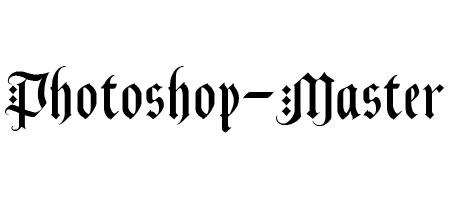
Дополнения Шрифты Татьяна Гапонова 25 июля 2009 Шрифт - BlackKnightFLF Красивый шрифт без поддержки русского языка. Скачать Шрифт - BlackKnightFLF
это штота новенькое..... на старый лад)))))